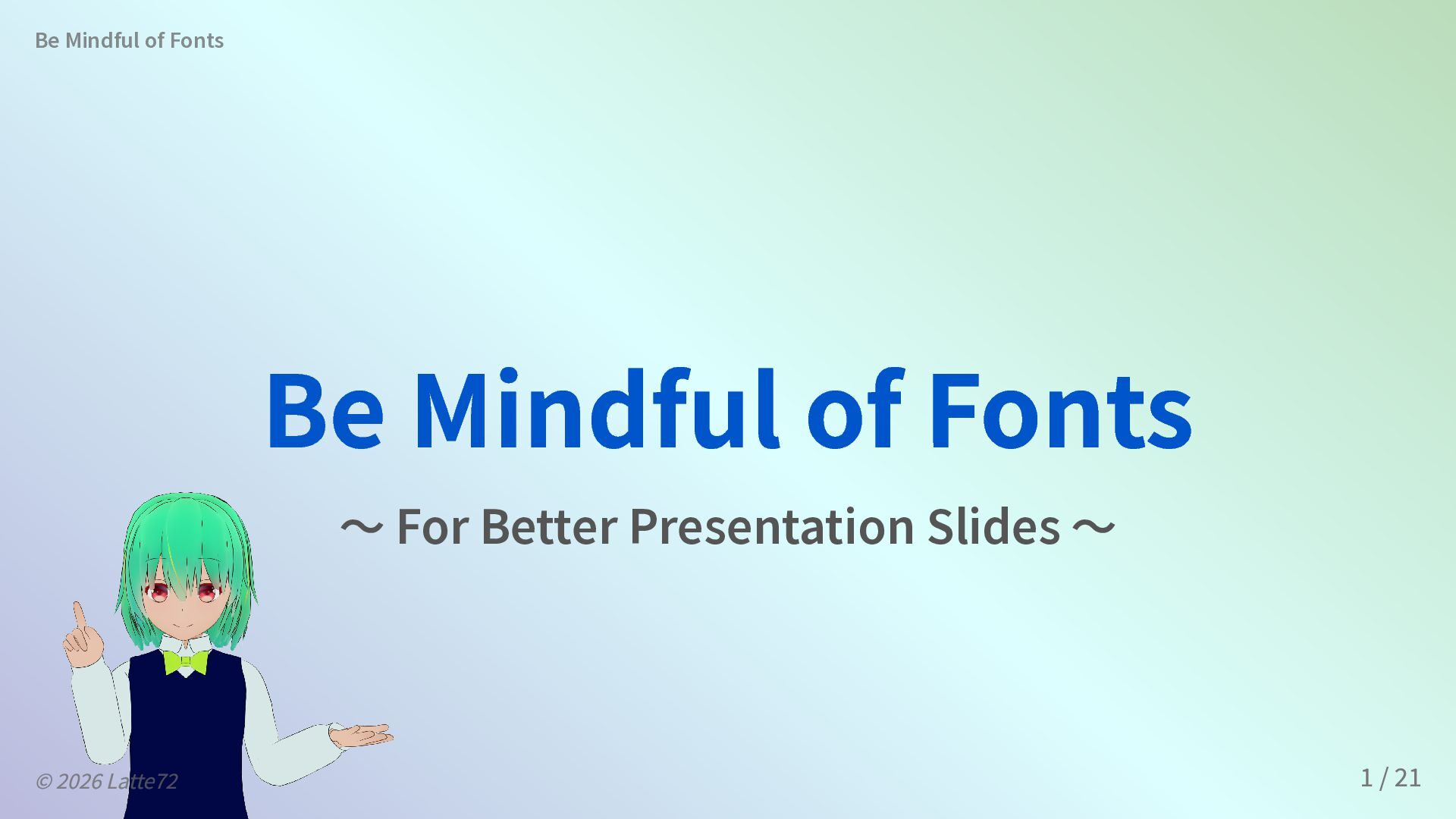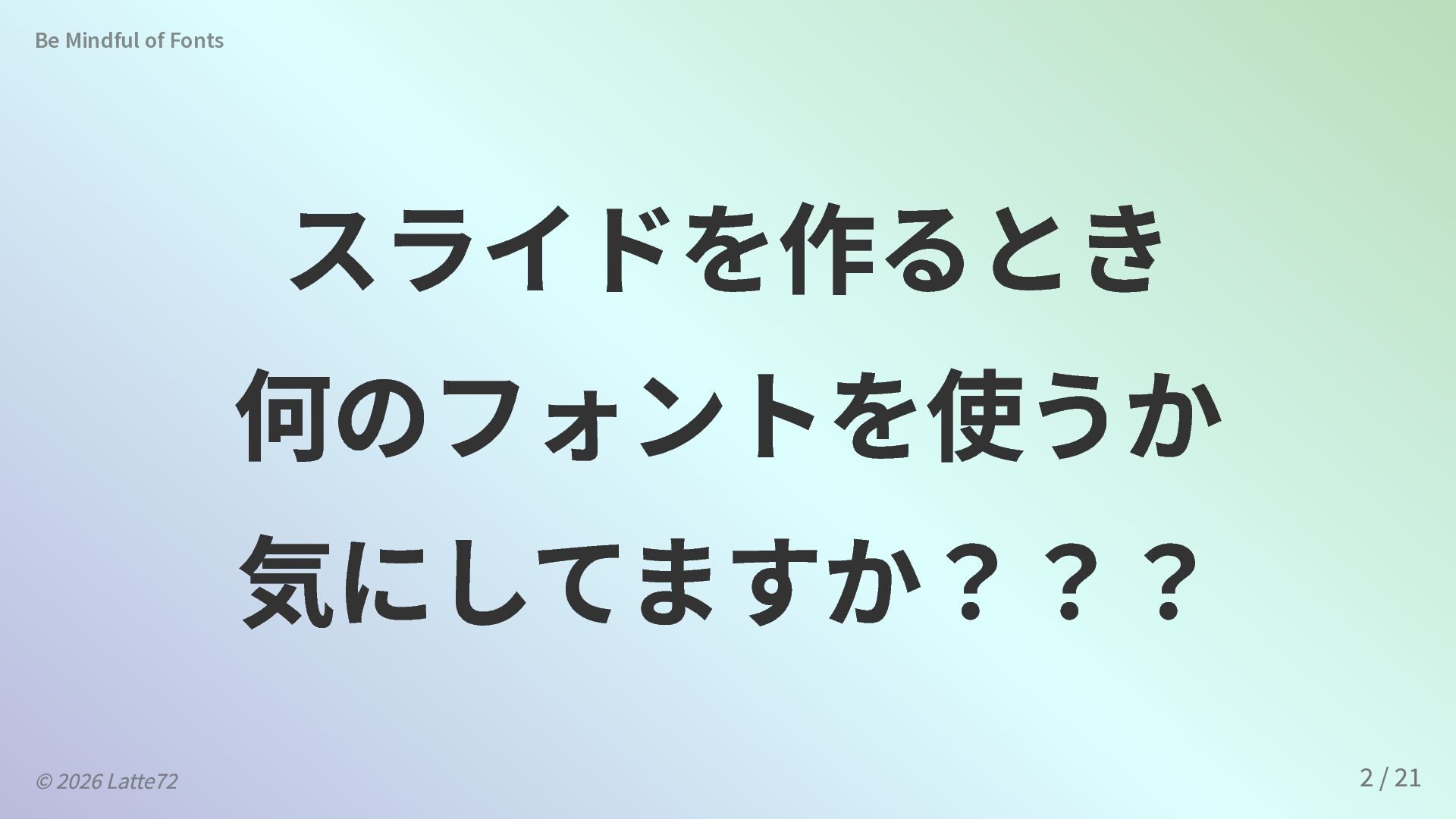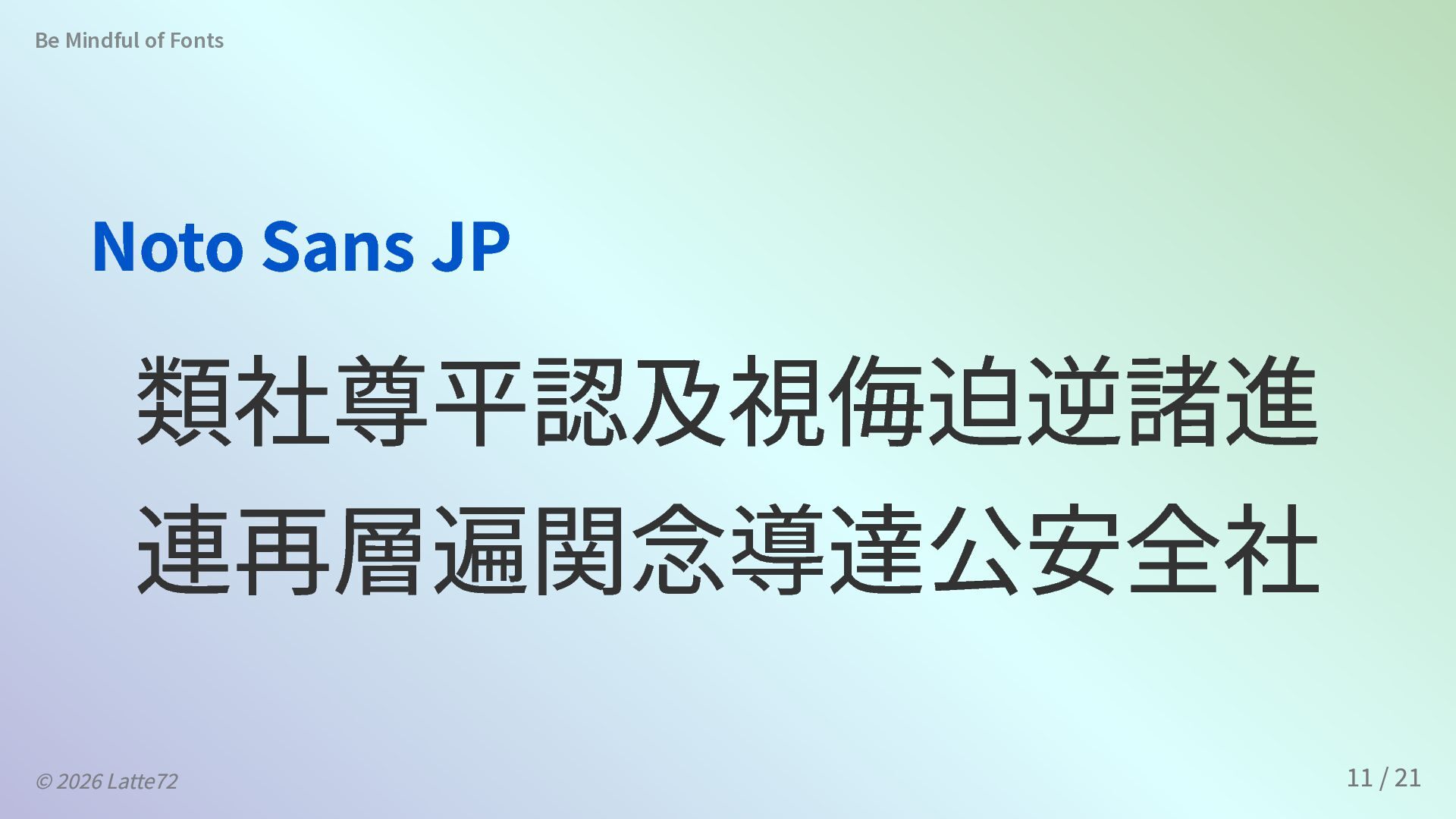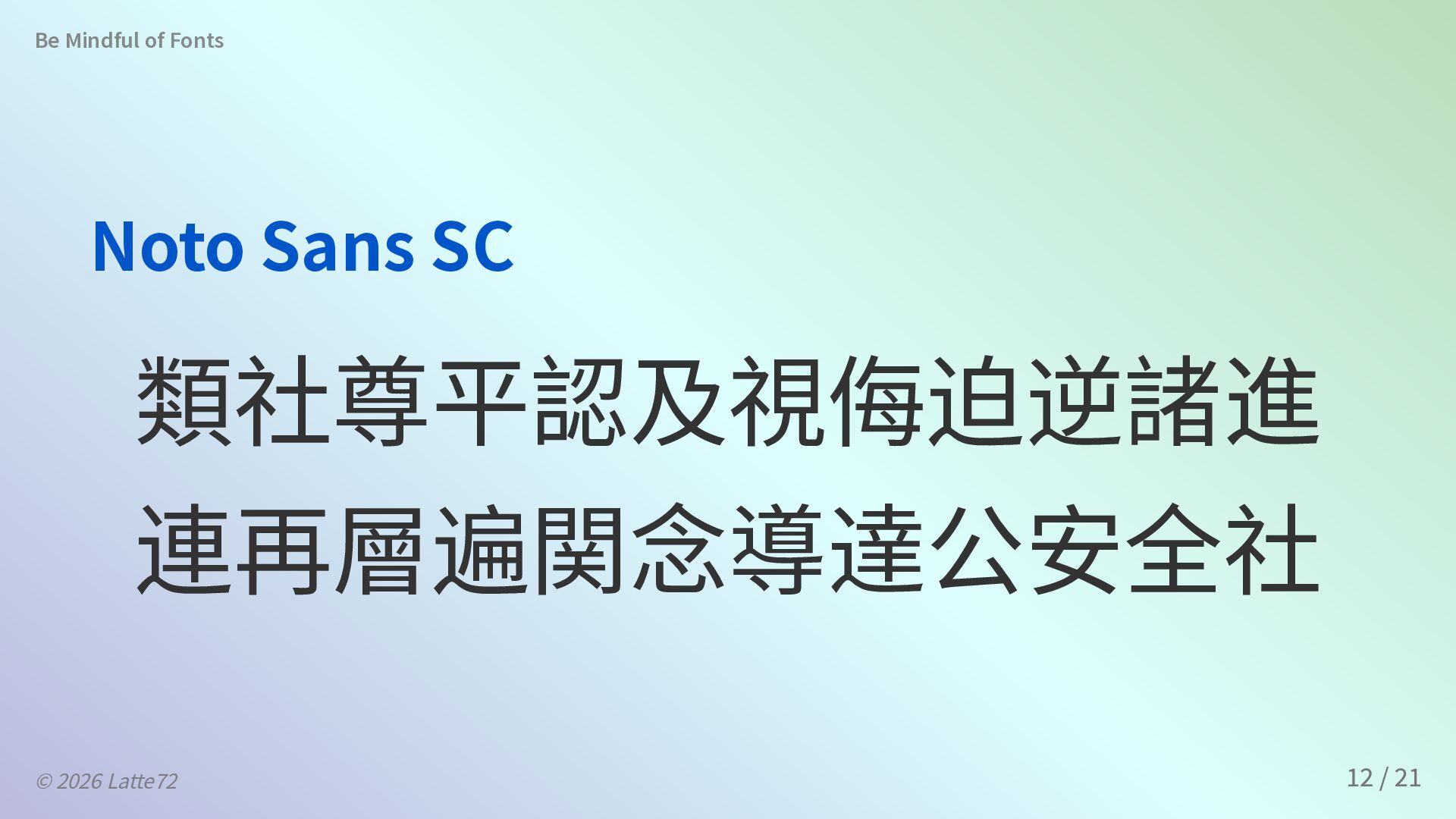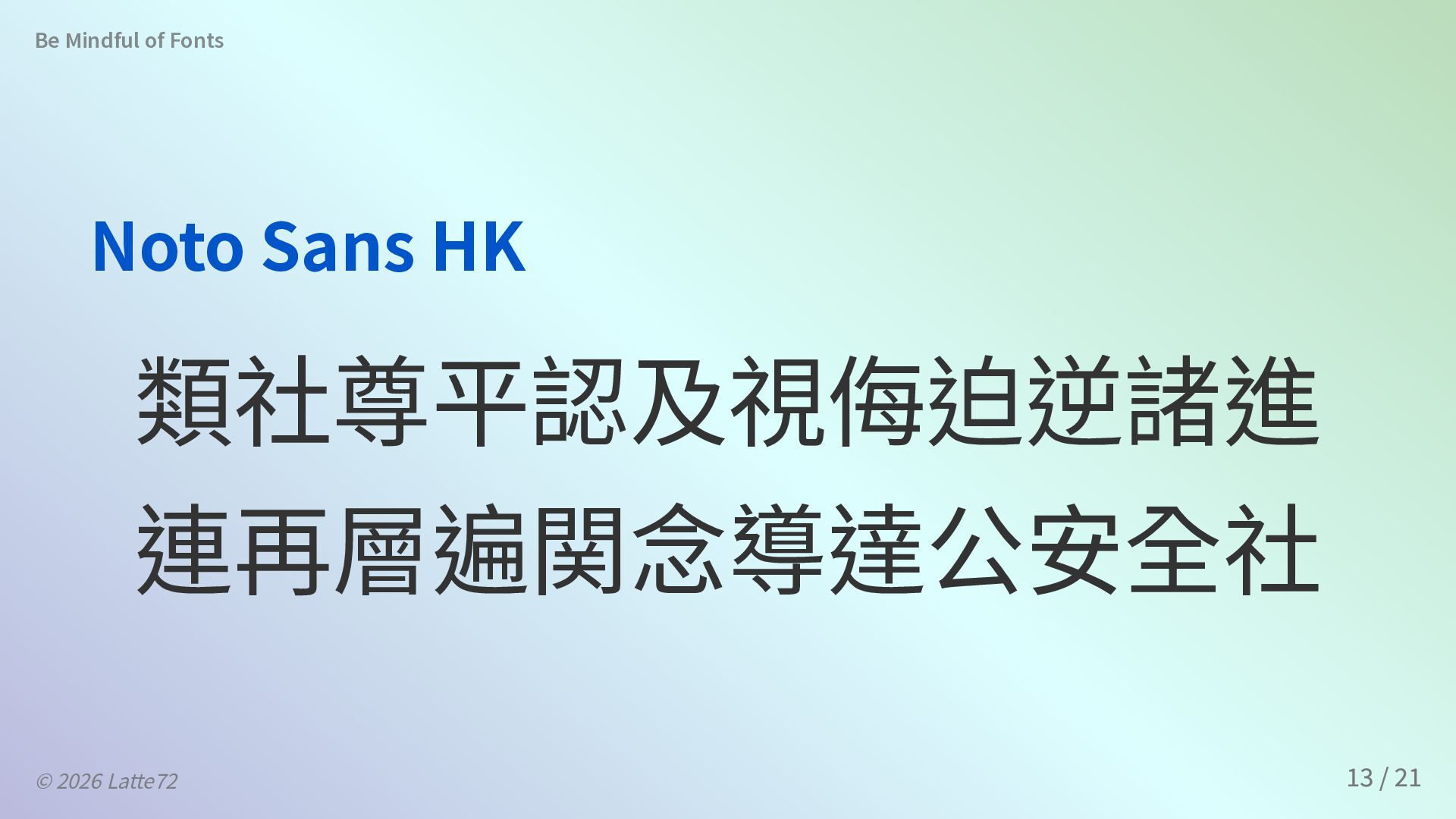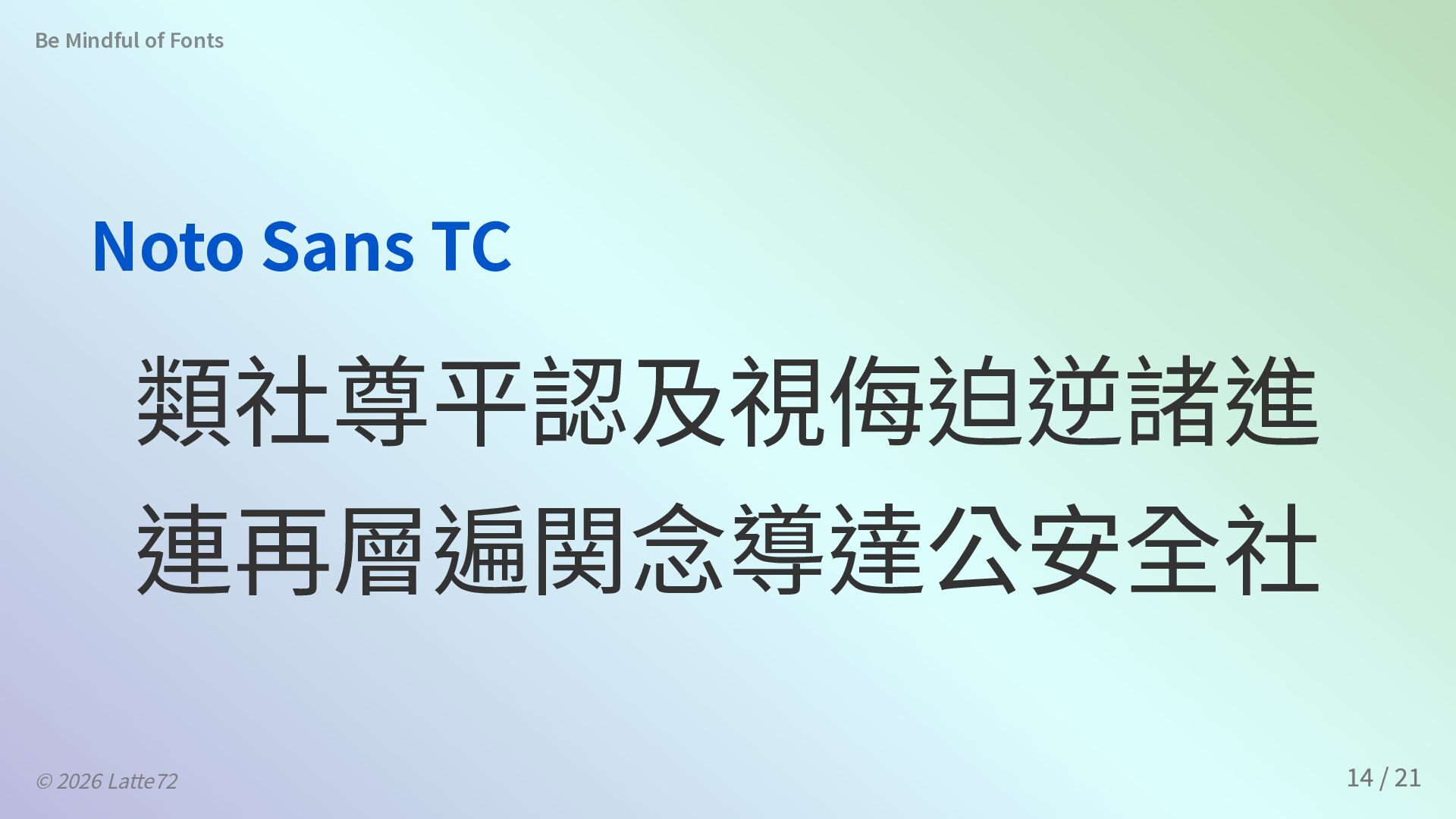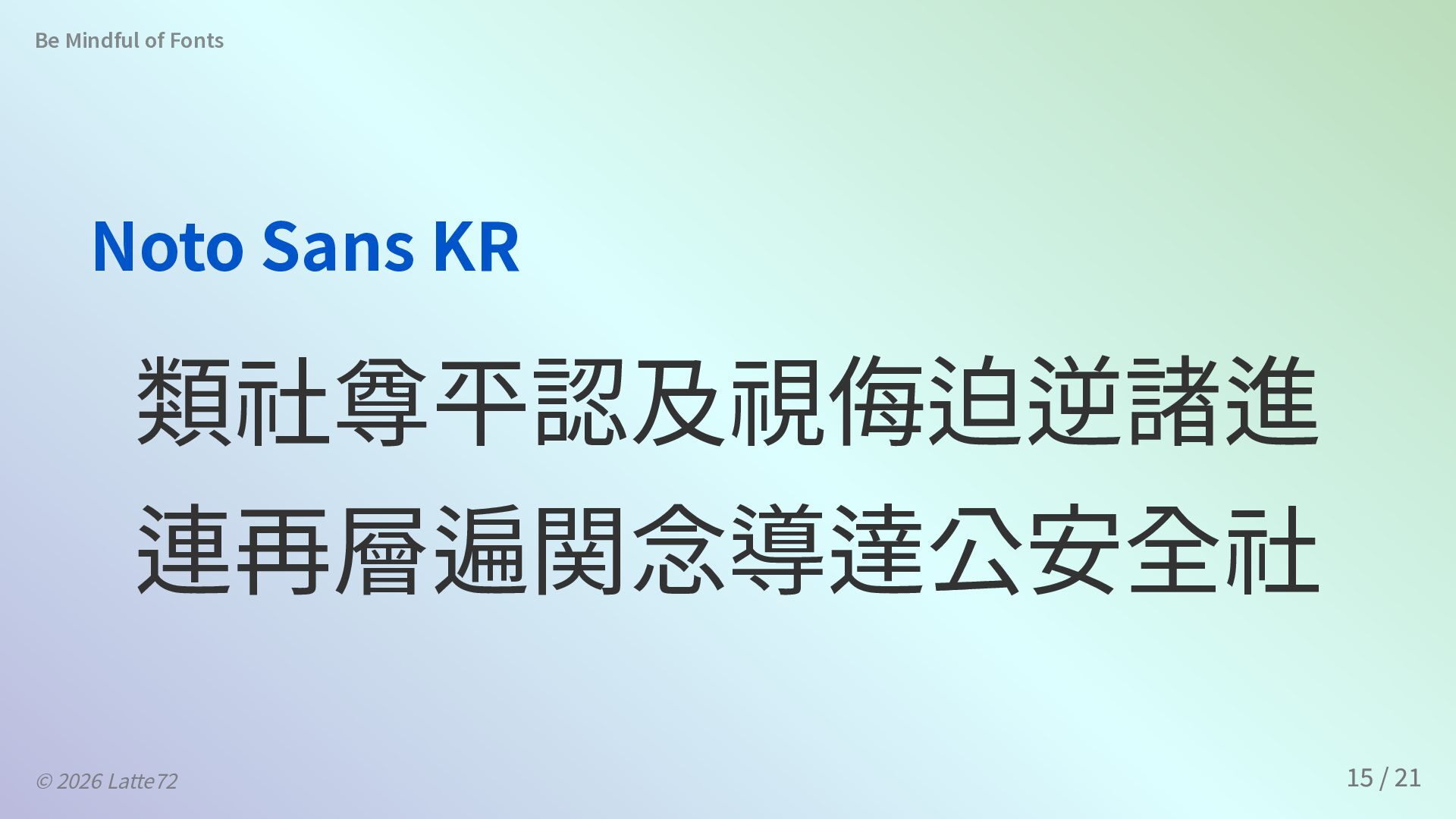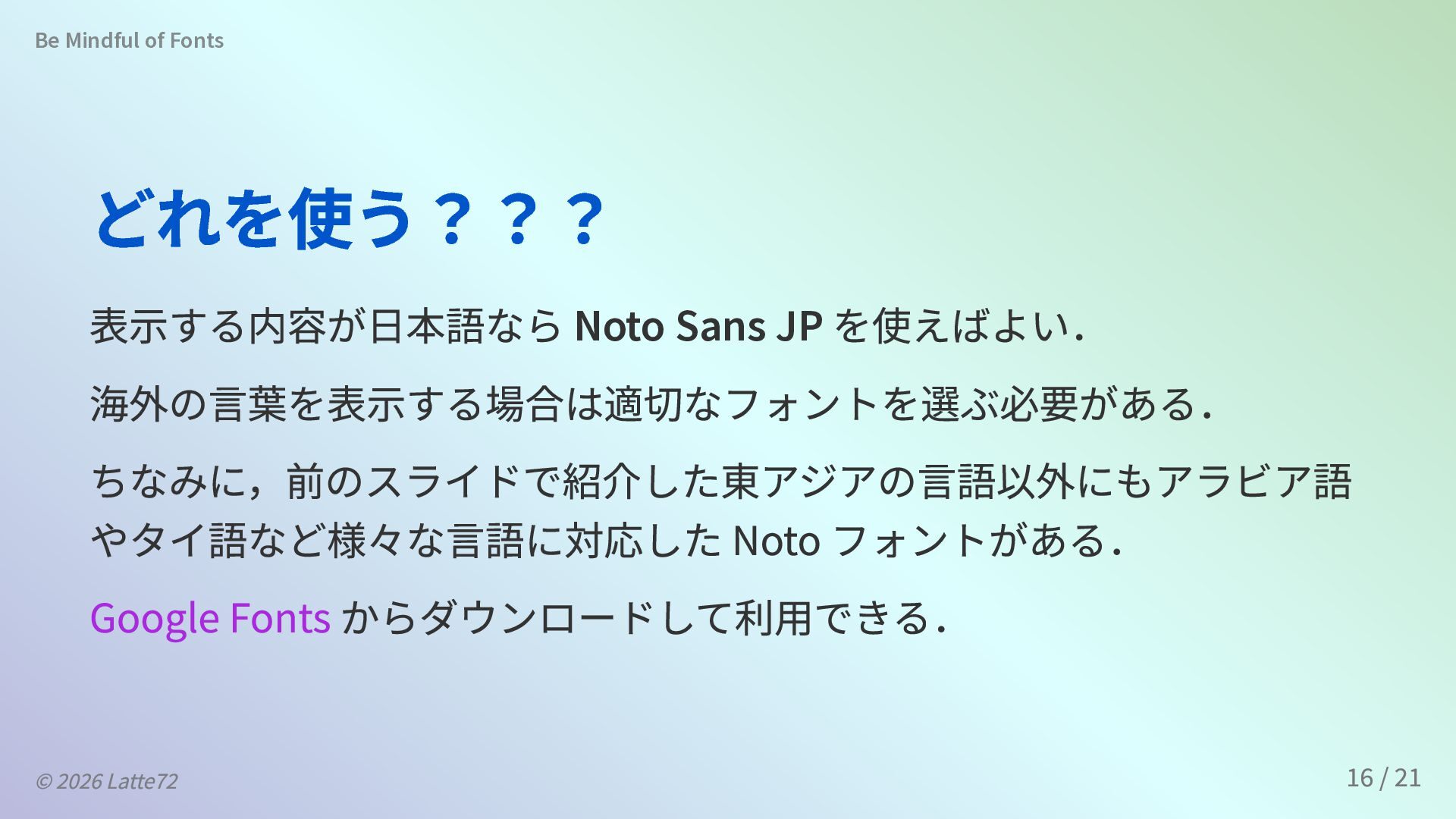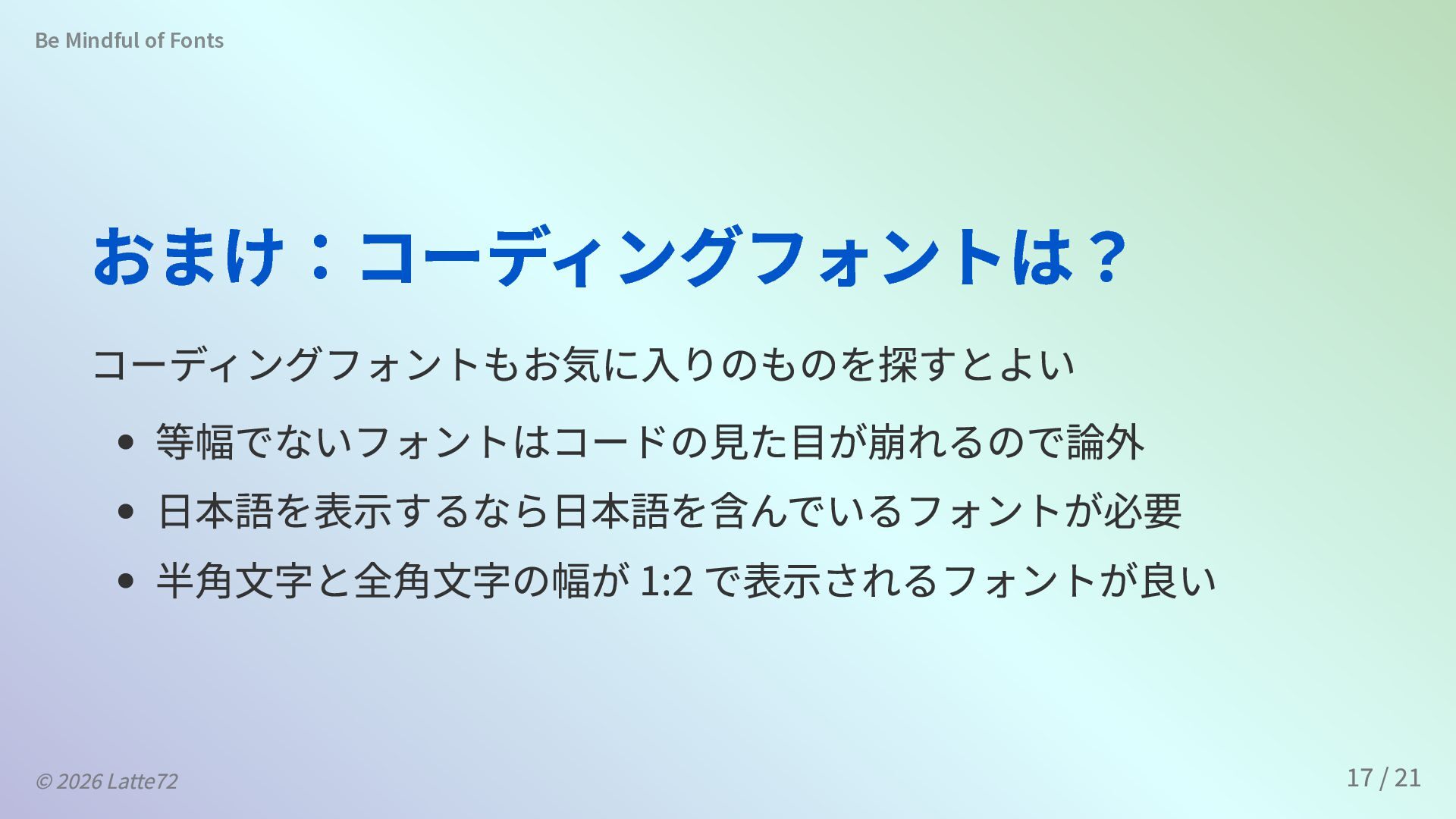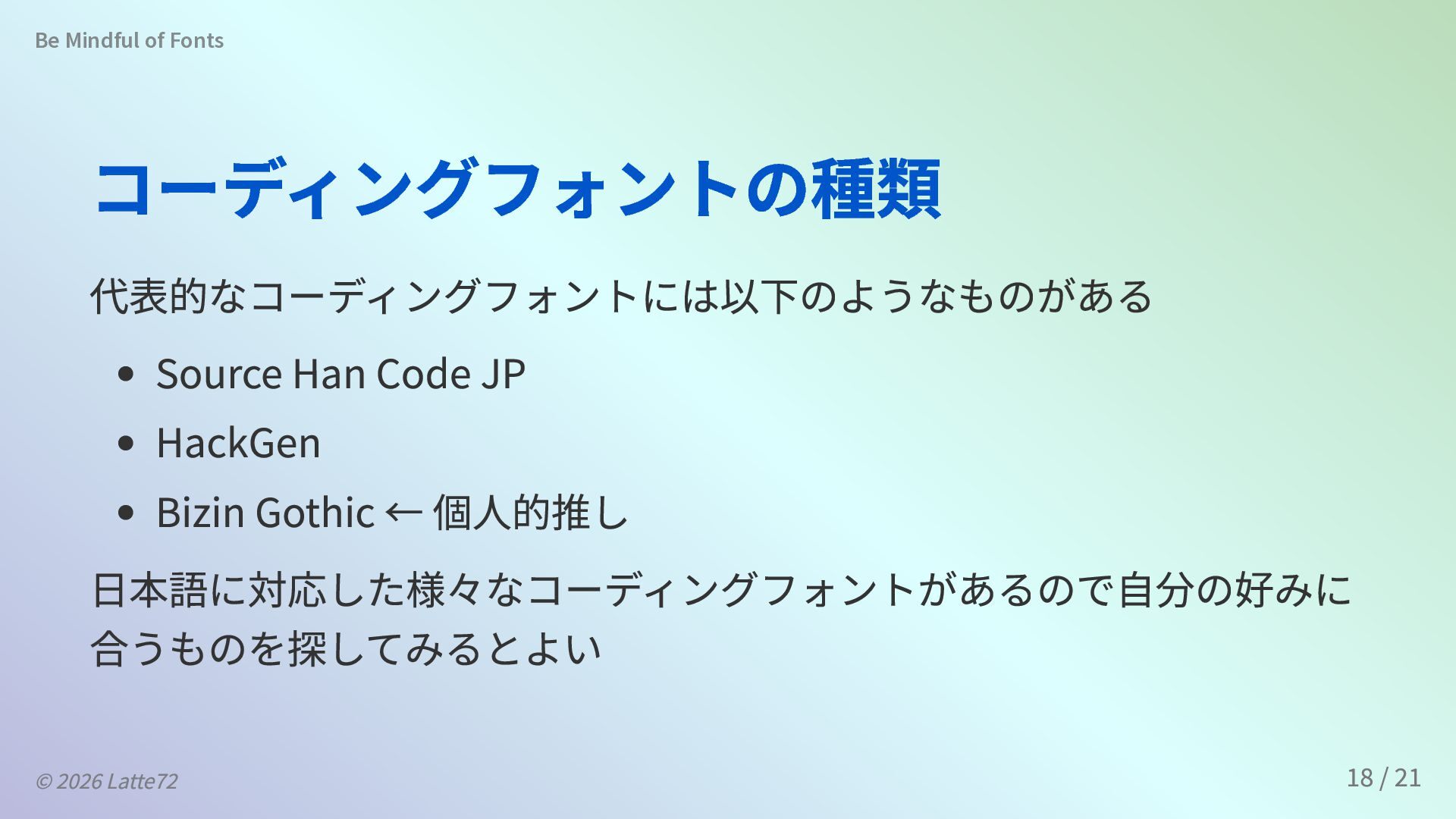
Be Mindful of Fonts
スライドやサイトを作るときにフォントにも注意を向けてほしいと思って書きました.
1. Be Mindful of Fonts ~ For Better Presentation Slides ~
2. そもそもフォントを気にしないのは論外 おすすめのゴシック体フォント Noto Sans JP ヒラギノ角ゴシック おすすめの明朝体フォント Noto Serif JP
ヒラギノ明朝 游明朝・游ゴシックはデザインが崩れやすいのであまり良くない Be Mindful of Fonts © 2026 Latte72 3 / 21
3. 設定しないとどうなる? Windows なら 游明朝・游ゴシック,メイリオ,Noto Sans CJK などが 使われることが多い. Mac や
iPhone / iPad なら ヒラギノ角ゴシック,ヒラギノ明朝などが使 われることが多い. Android なら Noto Sans CJK などが使われることが多い. Linux だと環境によっては日本語を表示できるフォントが入っていない こともある. Be Mindful of Fonts © 2026 Latte72 4 / 21
4. Noto には様々なバリエーションがある コンピューターで表示できない文字があり,豆腐(□)が表示される問 題を無くすために作られたのが Noto フォント.(No Tofu) 文字の形が異なる言語ごとに様々なバリエーションがある. Noto Sans
JP (日本語) Noto Sans SC (中国語簡体字・中国本土) Noto Sans HK (香港語) Noto Sans TC (中国語繁体字・台 湾) Noto Sans KR (韓国語) Be Mindful of Fonts © 2026 Latte72 10 / 21
5. コーディングフォントの種類 代表的なコーディングフォントには以下のようなものがある Source Han Code JP HackGen Bizin Gothic ←
個人的推し 日本語に対応した様々なコーディングフォントがあるので自分の好みに 合うものを探してみるとよい Be Mindful of Fonts © 2026 Latte72 18 / 21
6. Bizin Gothic #include <stdio.h> int main() { // 範囲は 1
から 30 まで for (int i = 1; i <= 30; i++) { // if 文で条件分岐して出力する文字列を決定 if (i % 15 == 0) printf("FizzBuzz\n"); else if (i % 3 == 0) printf("Fizz\n"); else if (i % 5 == 0) printf("Buzz\n"); else printf("%d\n", i); } } Be Mindful of Fonts © 2026 Latte72 19 / 21